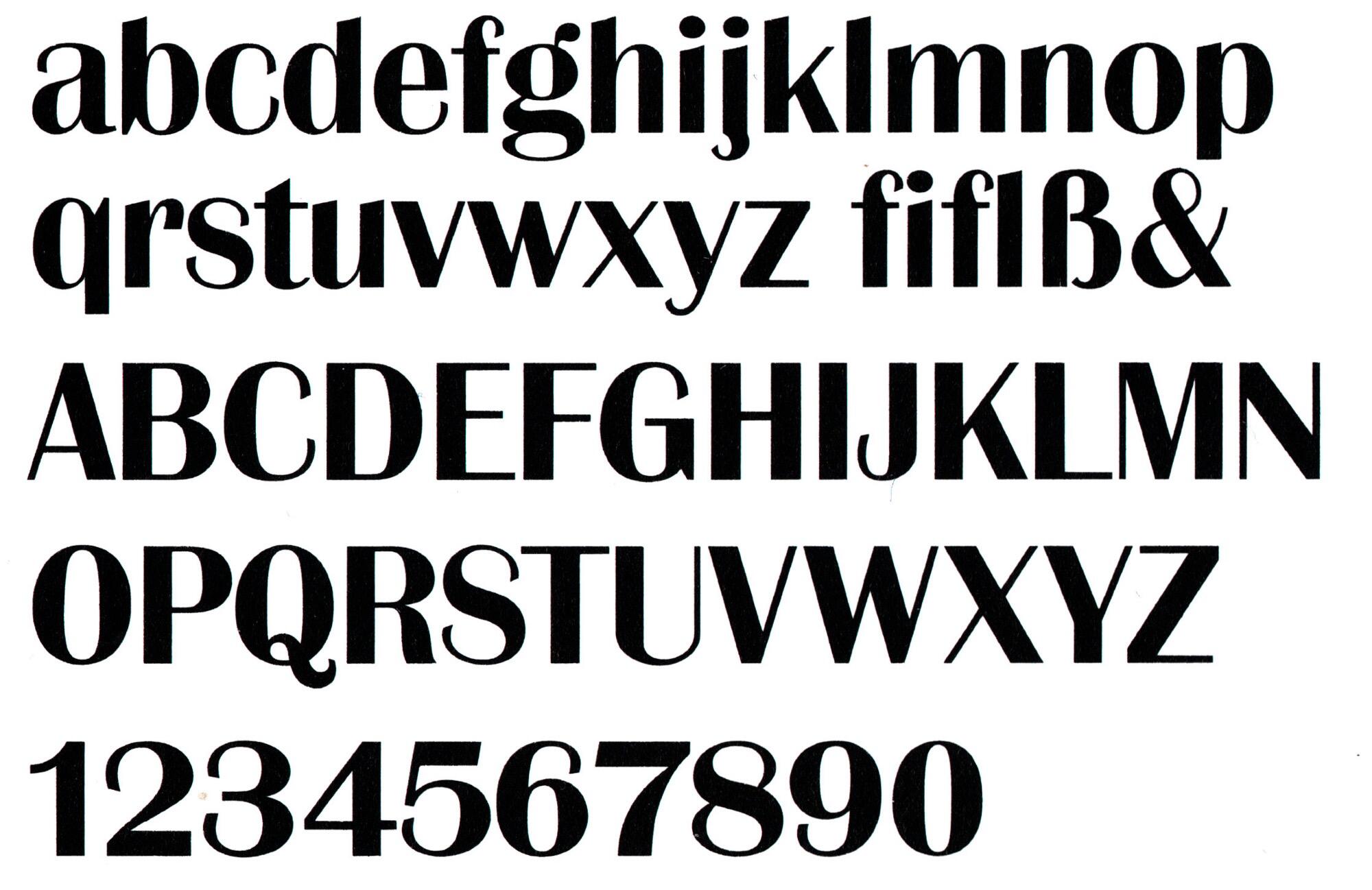
Font-Wiki: Britannic
Die Britannic erschien ab 1901 bei der englischen Gießerei Stephenson Blake. Die Schrift hat den typischen Duktus einer Antiqua, verfügt jedoch nicht über Serifen. Es erschienen zunächst zwei Strichstärken mit Kursiven. Die Schriftfamilie wurde auch für den Foto- und Digitalsatz übernommen.
Heute gibt es digitale Versionen in verschiedenen Ausbaustufen von URW, Elsner+Flake, Linotype und TypeShop (TS Grenoble).